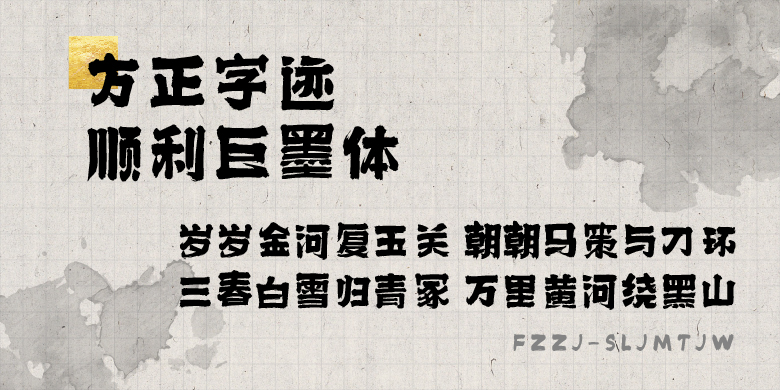
方正字迹-顺利巨墨体
方正字迹-顺利巨墨体,这款字体结构工整、笔画清晰,兼顾美观与易读性,适用于标题、正文、海报、包装、LOGO 等多种场景。字形优雅稳定,风格百搭耐看,适配日常排版与创意设计,让文字呈现更舒适、更具质感。方正字迹-顺利巨墨体一笔一画,皆是细节,以均衡的比例、流畅的线条打造舒适视觉体验,字形端正大气,风格简约现代。无论是商业设计、品牌宣传还是日常排版,都能轻松驾驭,让文字更有格调与力量。方正字迹-顺利巨墨体字体下载。
顺利巨墨体,笔墨厚重守拙,字重沉稳,字形中宫满盈,张力十足,有篆刻质感,变化魏隶笔画,合其大利,方块天地。并加强现代设计感和应用识别性。适合于标题大字、海报包装、品牌名称等。